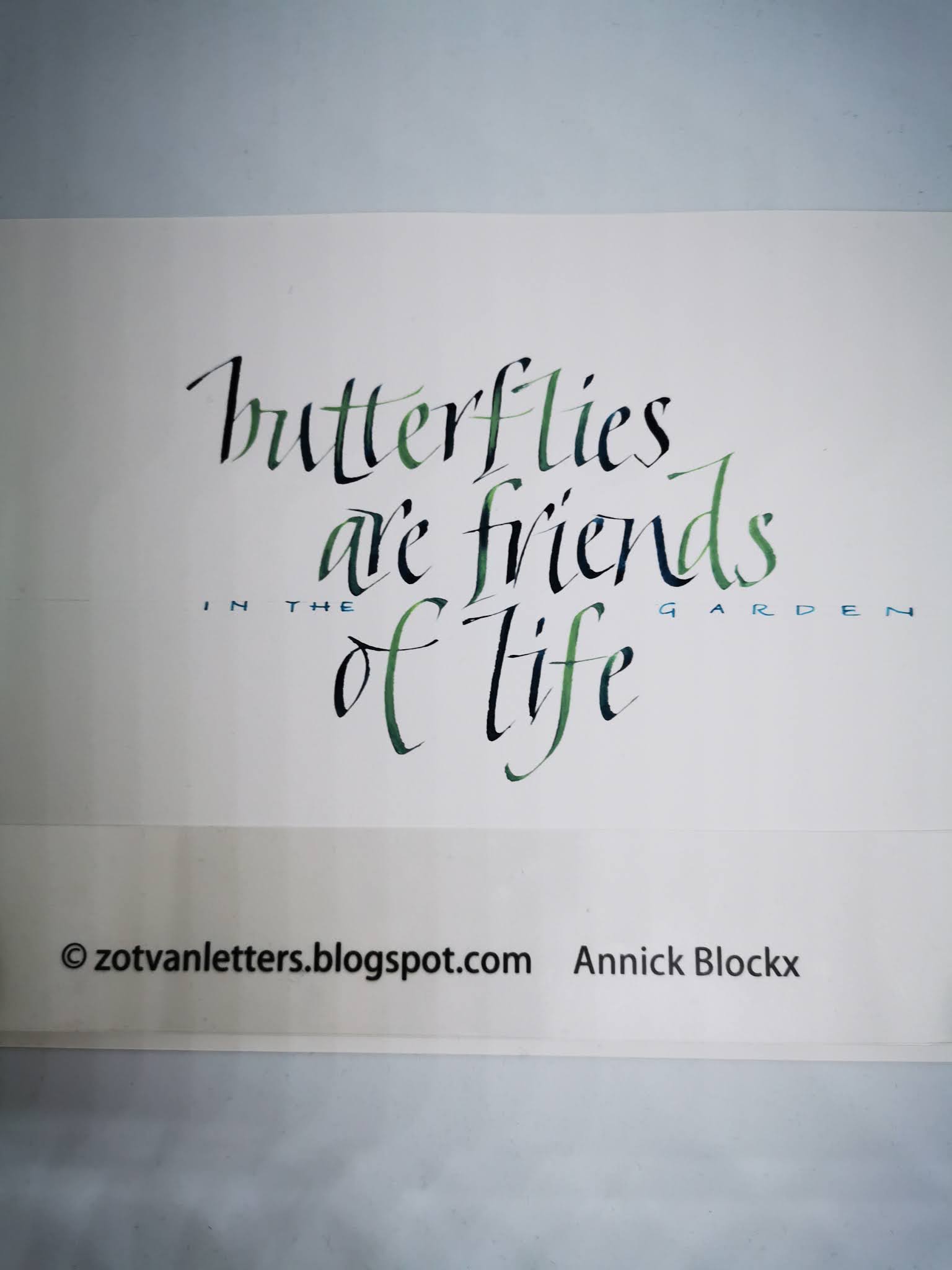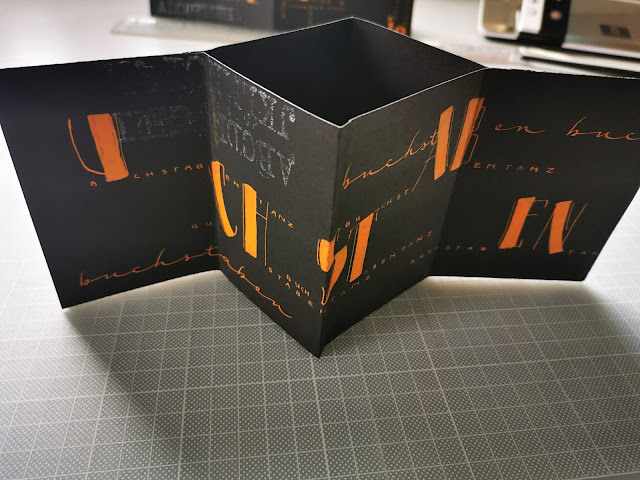
Een paar verjaardagskaartjes voor mijn voorraad in blauw en wit.
A few birthday cards for my stash in blue and white. I decorated the closure with a die-cut heart.
Een paar verjaardagskaartjes voor mijn voorraad in blauw en wit.
A few birthday cards for my stash in blue and white. I decorated the closure with a die-cut heart.
de drie sleutelwoorden van de november-opdracht waren :
the three key words for November's issue were:
1) kontrast of tegenstelling - contrast
2) letterdans - letter dance
3) paars en geel - purple and yellow
Paars en geel vind ik niet zo mooi samen, dus wilde ik eens testen wat het zou geven als ik ze zou mengen....
I don't really like the combination of purple and yellow , but what if I tried to mix them ?
| een soort van oranje-oker / a kind of orange-ochre |
Met deze kleur schreef ik met de trekpen een paar grote letters van 4 cm hoog (B-U-C-H-S-T-A-B-E-N-T-A-N-Z). Het duitse woord voor letterdans.
I used this new gouache paint and a ruly pen to draw a few letters (4 cm ), the German word for letter dance.
En dan voegde ik ook kontrast toe door kleinere letters toe te voegen (1.5 mm) en een paar alfabetstempels
I created contrast by adding smaller letters (1.5 mm) and a few (parts) of alfabet stamps.
Hier is een kort filmpje - and a short video to end with.
De tekst is geschreven met Brause pen 2.5 in blauw-grijze gouache.
Spijtig genoeg heb ik er de laatste tijd heel wat van nodig gehad.
On top of this card is a piece of silk print (made by a friend) of which some parts are softly coloured with pencils (Derwent). I wrote the text with a Brause pen of 2.5 and blue-grey gouache.
Veel schrijf-knip-en plakwerk om mijn ontwerp goed te krijgen...
Writing-cutting and pasting to get the design just right ....
"butterflies are friends in the garden of life" (author unknown- auteur onbekend)
Dan 3 tinten gekozen uit dit kleurenpalet :
| chose 3 colours from this colour chart |
En dan uitgeschreven. The final exercises:
| 1ste versie: f+f+l zijn verbonden- 1st version in which f+f+l are connected |
| in deze versie gebruikte ik ook het groen- I also used the green shade in this one |
| en in deze speelt het groen de hoofdrol met telkens bovenaan een tikje blauw- the green in the lead in this last exercise -only used the blue on top of every letter |
Welke is jullie favoriet ?
I don't know yet which I like best. Have you got a favourite ?